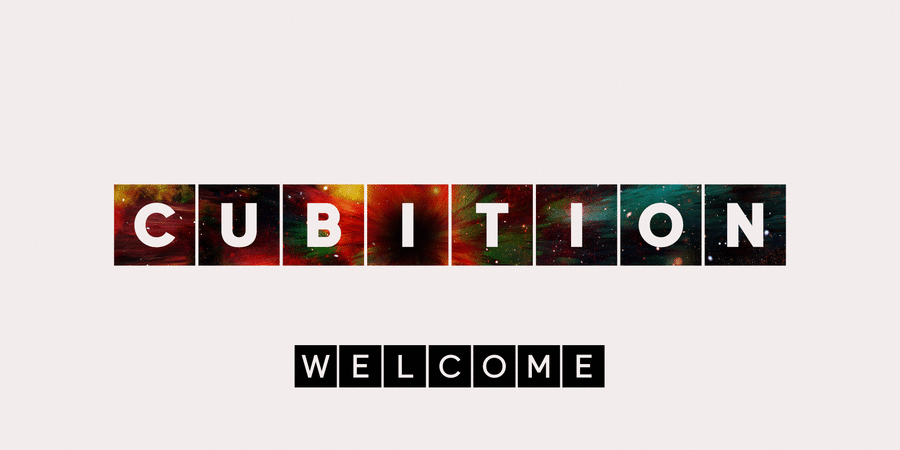
Сімейство шрифтів Cubition створено на основі шрифту без зарубок Everest Pro. Він чудово підходить для графічного дизайну та використання на дисплеях, а також ідеально підходить для фірмової символіки, журналів, газет, книг, веб-сайтів і реклами.
Шрифт розробив Микола Савчук у 2021 році.
Асоціації з сімейством шрифтів CubitionОсобистість і характер гарнітури:
мінімалістичний, чіткий, делікатний, легкий, прохолодний, свіжий, тонкий, лаконічний, ясний, рівний, якісний, невагомий, прозорий, логічний, точний, повітряний, скляний, гострий, дротяний, міський, статичний, худий, твердий, зрозумілий, доступний, елементарний, правильний, формальний, серйозний, стійкий, стабільний, самостійний, відповідальний, західний, діловий, холодний, спокійний, сучасний, модний, глобалізований, глобалістічний, креслярський, інженерний, чистий, помірний, стандартний, універсальний, розумний, квадратний, тісний, чорний, Простий, нейтральний, значний, обов'язковий, солідний, сильний, важкий, переконливий, важливий, урбаністичний, надійний, впевнений, гучний, кондовий, мужній, різкий, робочий, промисловий, суворий, технічний, індустріальний, яскравий, помітний, щільний, активний, машинний, техногенний, крутий, амбітний
парфумерія, туалетна вода, шампунь, косметика, мода, дієта, дизайн, гігієна, чистота, Місто, суспільство, аеропорт, метро, навігація, інновації, архітектура, наука, одяг, реклама, магазин, медицина, взуття, креслення, інженер, прилад, математика, вода, торгівля, конструктор, коворкінг, гра, розваги, шоу, іграшка, телебачення, урбаністика, будівництво, машинобудування, охорона, тренажери, вантажівка, далекобійник, електростанція, завод, цегла, порт, сейф, ремонт, захист, екскаватор, робочий Гарнітура має ознаки стилів: